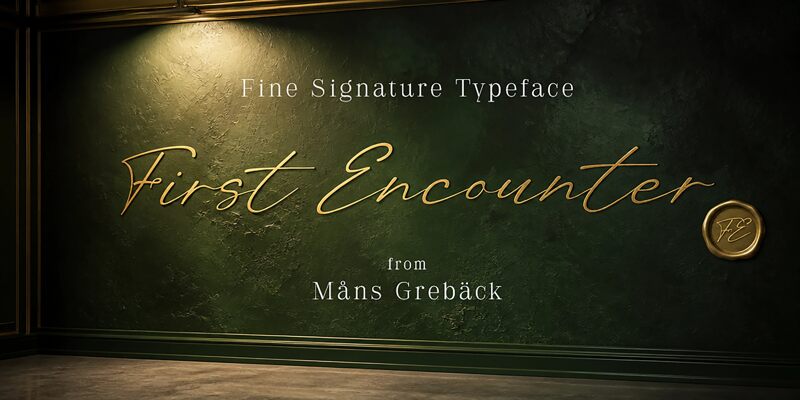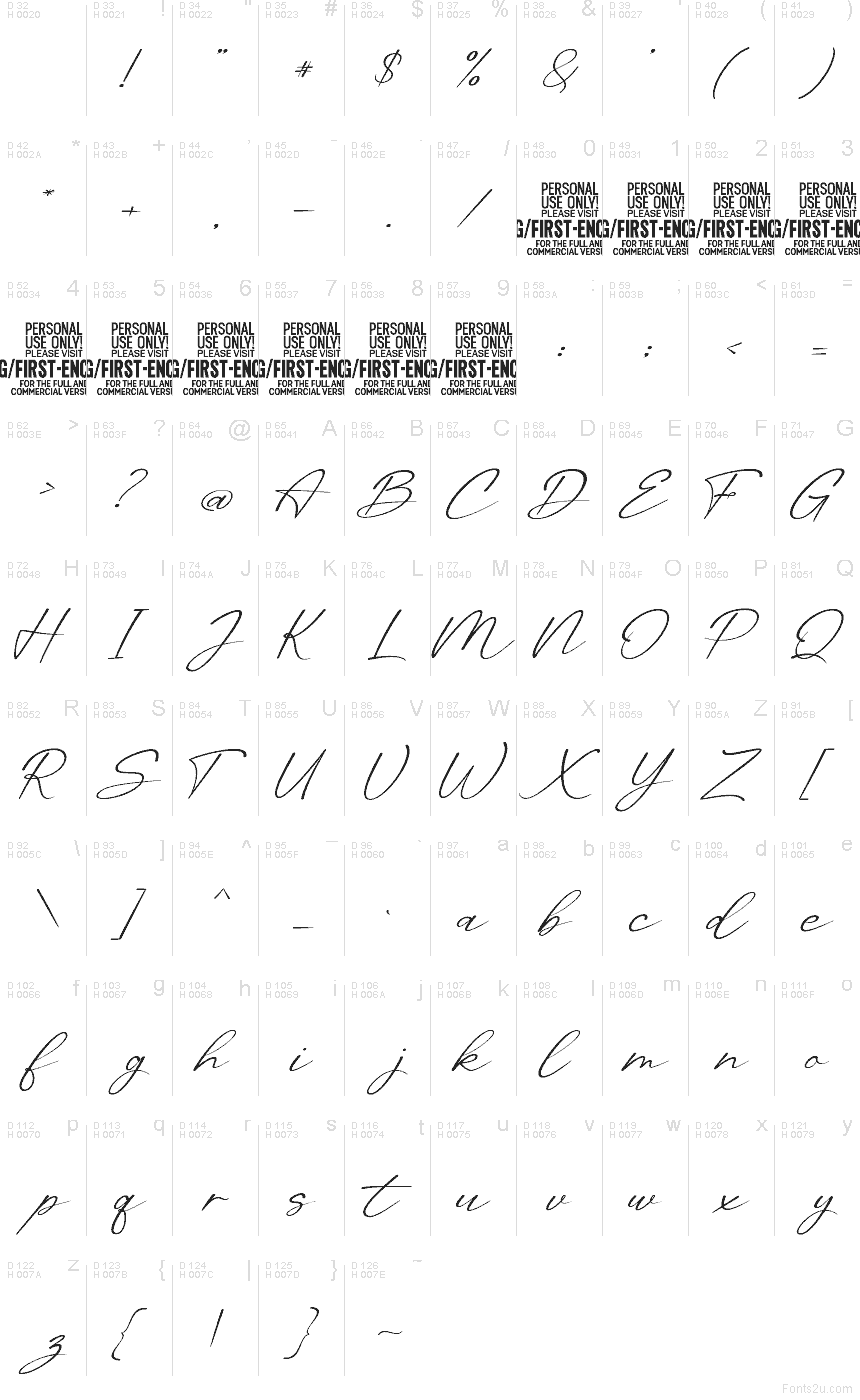
First Encounter de Mans Greback é uma fonte de assinatura gratuita com traços longos e fluidos e uma postura fortemente inclinada. As letras são desenhadas levemente, com mudanças rápidas de direção e laços generosos que sugerem uma caligrafia confiante. Suas junções irregulares e traços cruzados estendidos mantêm a escrita com um tom pessoal em vez de formal.
Como uma marca manuscrita, ela pode conferir uma elegância feita à mão a identidades visuais de moda, convites de casamento ou embalagens de cosméticos. Os gestos também se adequam a capas de álbuns e sinalização de boutiques, onde as letras podem se tornar parte de um emblema em vez de servir apenas como um rótulo.
First Encounter é uma fonte manuscrita de assinatura.